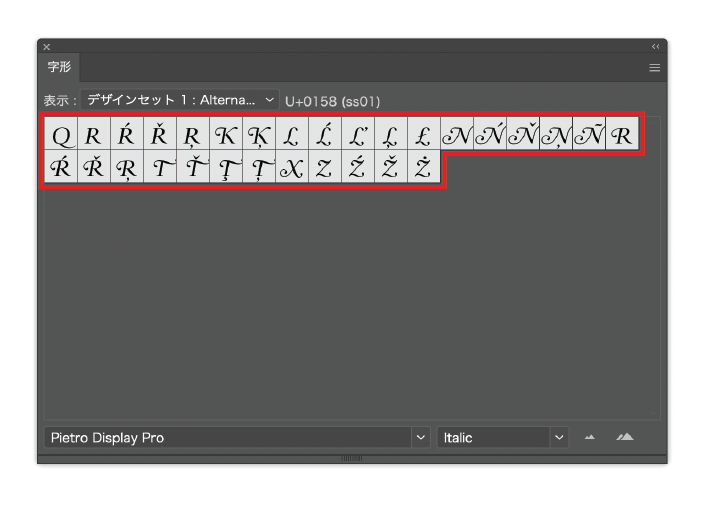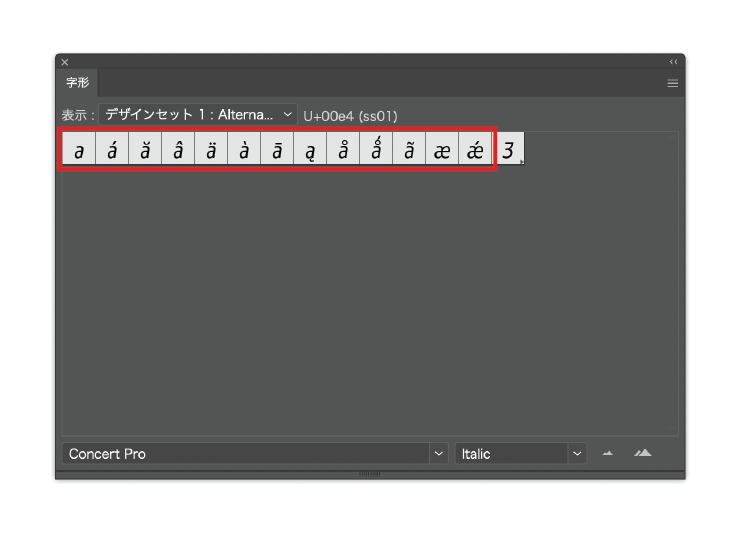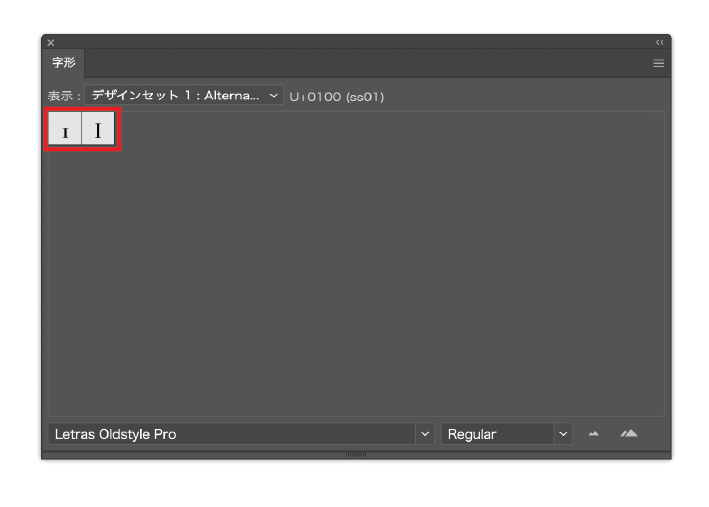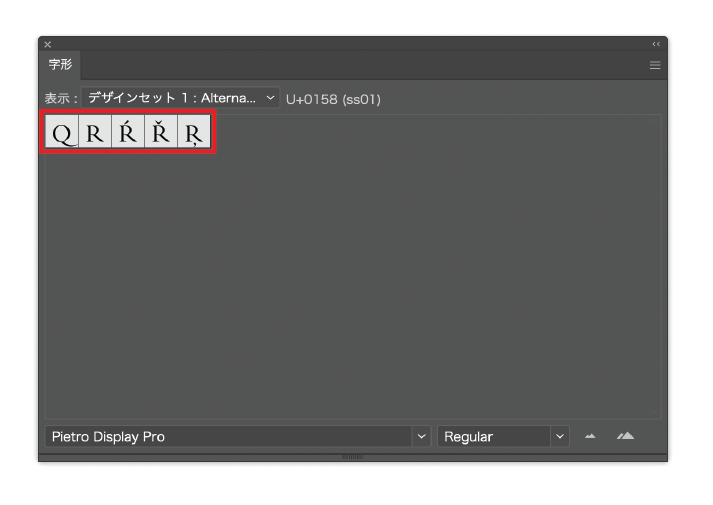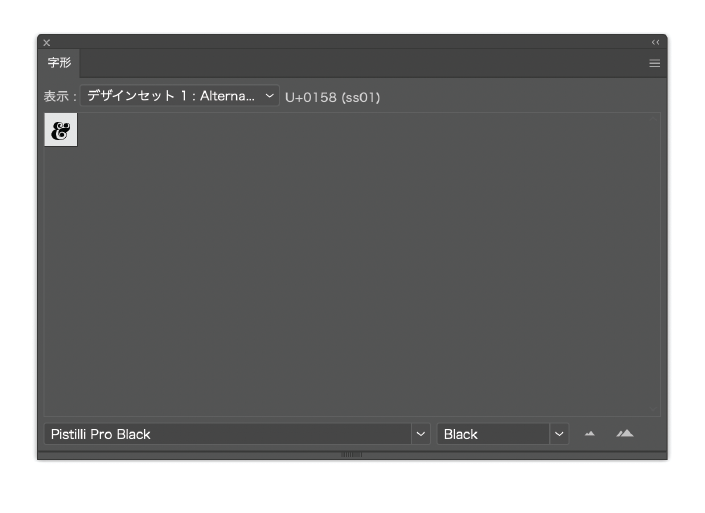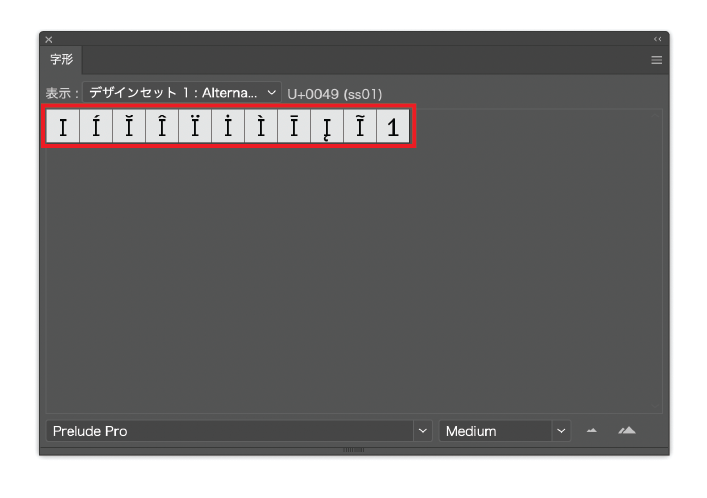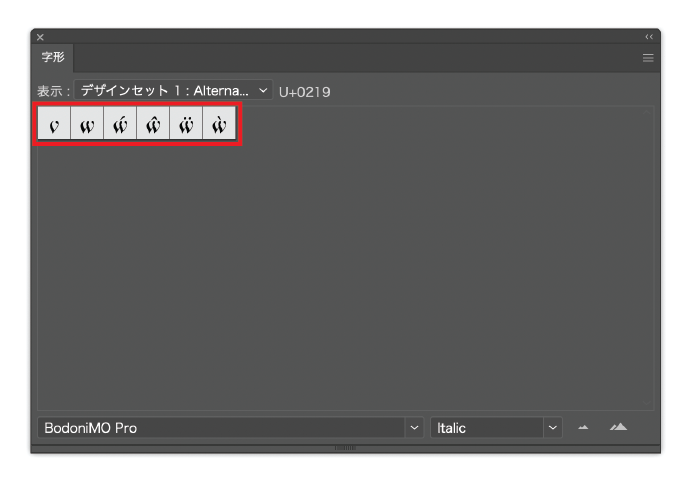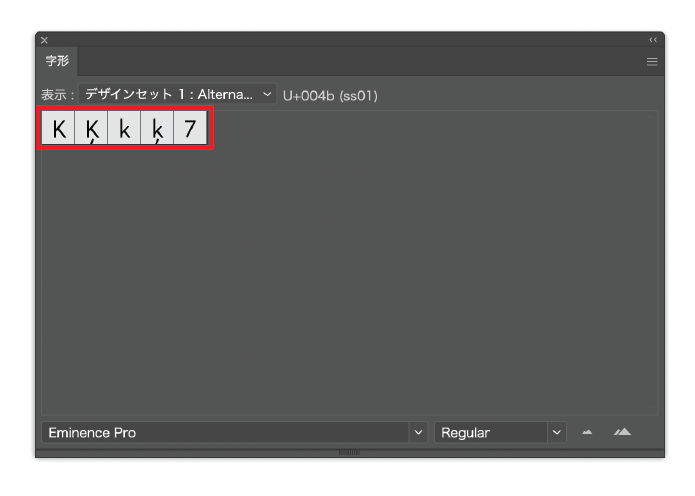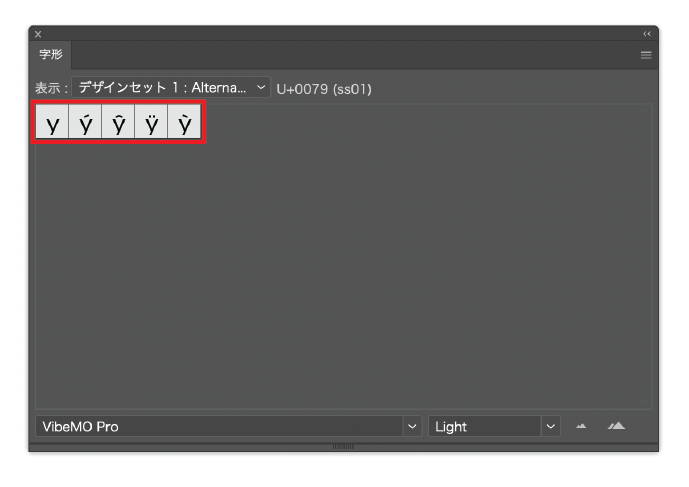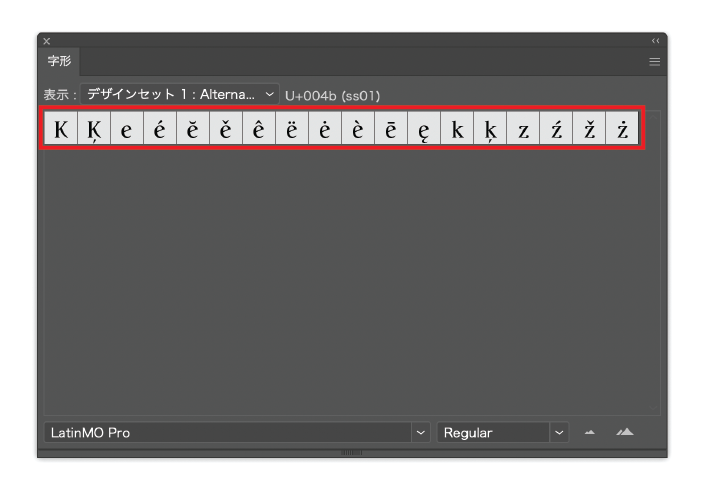
一部欧文書体の設定情報に誤りがあり、スタイルセットの名称と実際の挙動に食い違いがありました。
この現象はフォントの改訂によって解決されます。
スタイルセットとは、OpenTypeフォントの字形切り替え機能です。フォントごとに設定された代替字形のグループを呼び出します。
【内容】
対象フォントでは「Alternate Figure 3」という名前のスタイルセットが用意されていますが、「Alternate Figure 3」を有効にした際、スタイルセット名称から予想される代替字形(算用数字の3の別デザイン)ではなく個々のフォントごとに異なる代替字形のグループが呼び出されます。
以下では「Alternate Figure 3」で呼び出される字形の例と、その対象フォントをご説明します。
二階建ての「a」
| 改訂前スタイルセット名 | 改訂後スタイルセット名 |
| Alternate Figure 3 | Two-storey a / Alternate Figure 3 |
数字の「1」の別デザイン
| 改訂前スタイルセット名 | 改訂後スタイルセット名 |
| Alternate Figure 3 | Alternate Figure 1 |
ロングテールの「Q」と「R」
| 改訂前スタイルセット名 | 改訂後スタイルセット名 |
| Alternate Figure 3 | Uppercase Q and R with Tail |
ロングテールの「Q」と「R」およびスワッシュ字形
| 改訂前スタイルセット名 | 改訂後スタイルセット名 |
| Alternate Figure 3 | Alternate Capitals with Swash |
「&」(アンパサンド)の別デザイン
| 改訂前スタイルセット名 | 改訂後スタイルセット名 |
| Alternate Figure 3 | Alternate Ampersand |
バーのついた「I」(大文字のアイ)と数字の「1」
| 改訂前スタイルセット名 | 改訂後スタイルセット名 |
| Alternate Figure 3 | Uppercase I and Figure 1 with Serif |
小文字の「v」と「w」
| 改訂前スタイルセット名 | 改訂後スタイルセット名 |
| Alternate Figure 3 | Alternates for Lowercase v and w |
「K」と「k」および数字の「7」の別デザイン
| 改訂前スタイルセット名 | 改訂後スタイルセット名 |
| Alternate Figure 3 | Alternate K / Figure 7 |
小文字の「y」
| 改訂前スタイルセット名 | 改訂後スタイルセット名 |
| Alternate Figure 3 | Alternate Lowercase y |
その他さまざまなデザインバリエーション
| 改訂前スタイルセット名 | 改訂後スタイルセット名 |
| Alternate Figure 3 | Stylistic Alternates |
正しい代替字形のグループが呼び出されるよう改訂いたします。
スタイルセット名の改訂を行います。